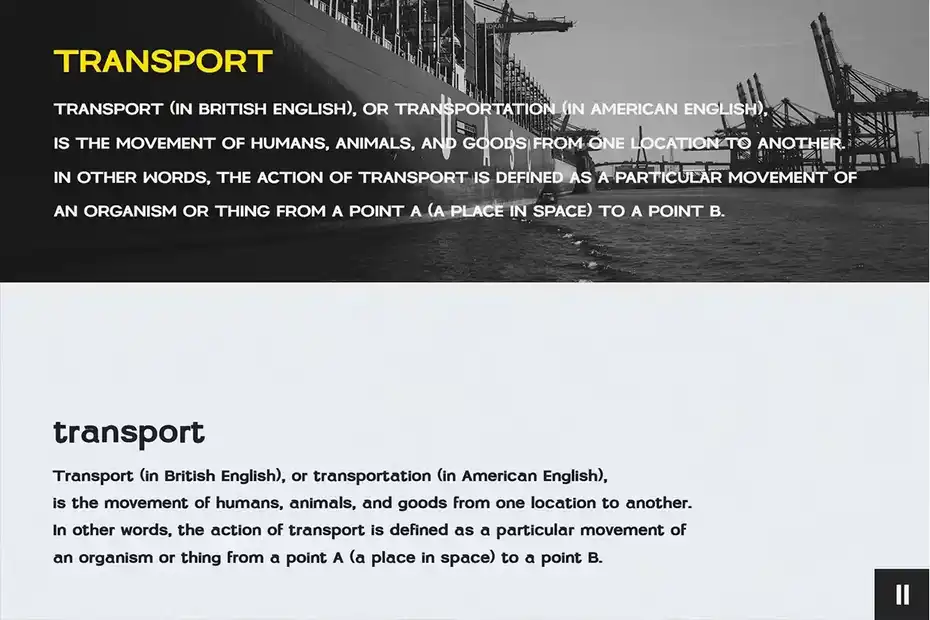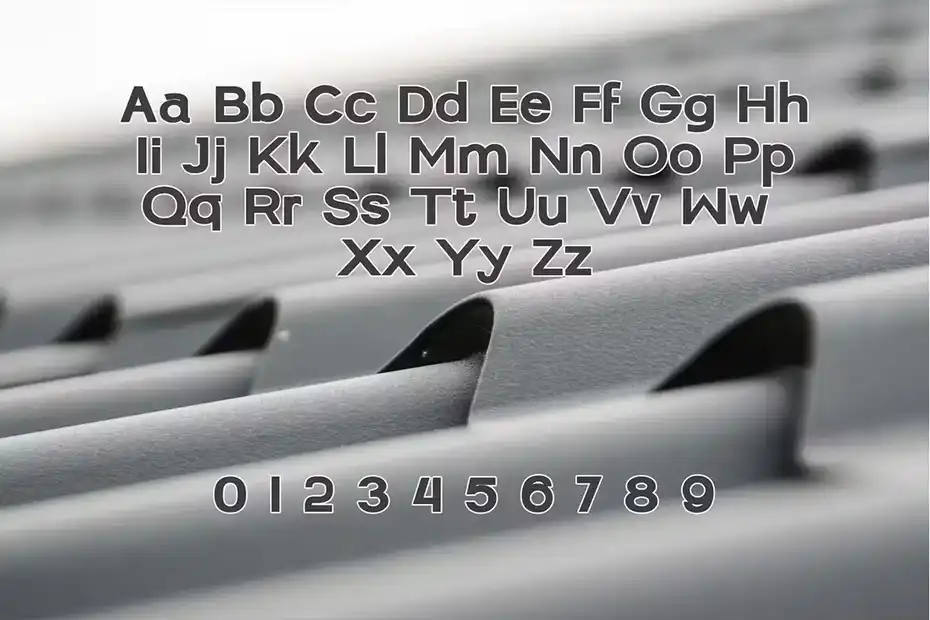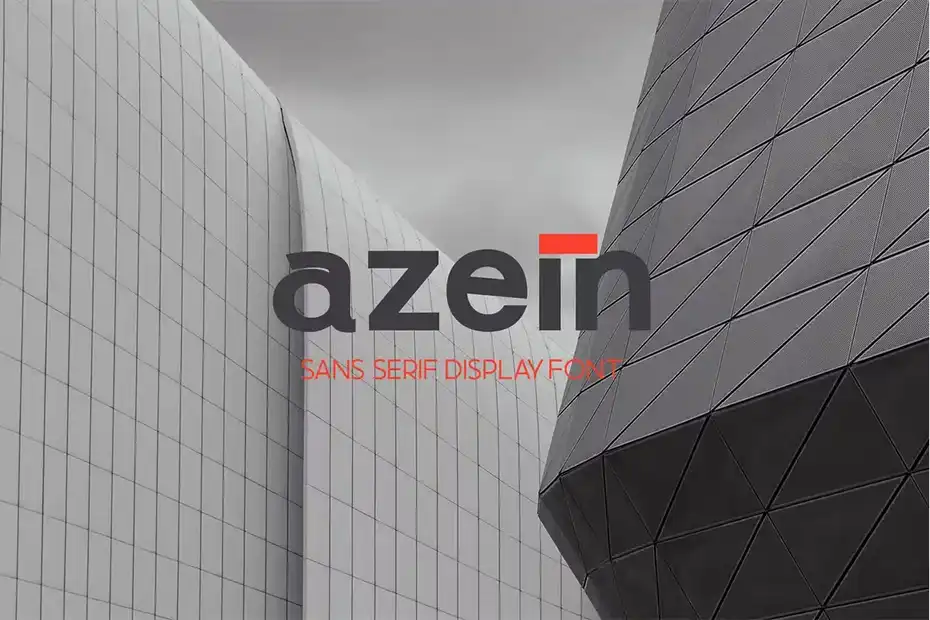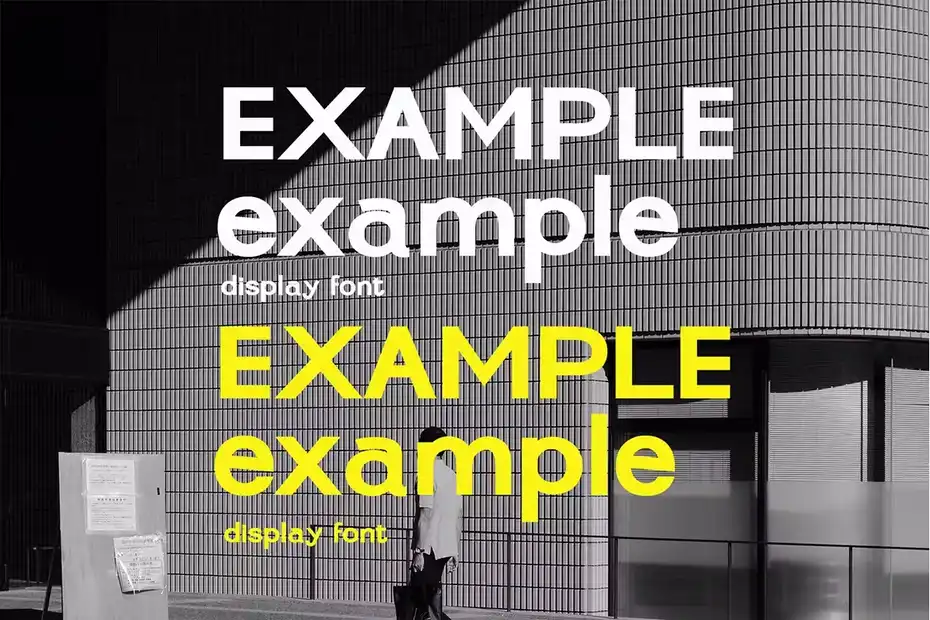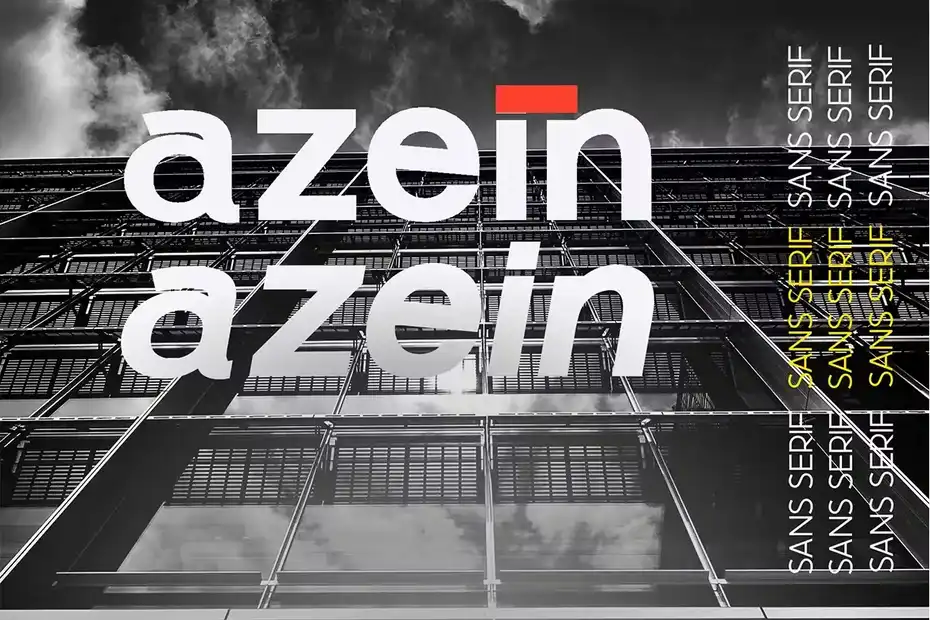
دانلود فونت ساده مدرن Azein – Modern Simple Font
دانلود فونت ساده مدرن Azein – Modern Simple Font : این مجموعه شامل یک فونت انگلیسی ساده و مدرن است که برای لوگو، مجله، پست و استوری شبکه اجتماعی، بروشور و غیره مناسب میباشد.
• عنوان مجموعه: Azein – Modern Simple Font